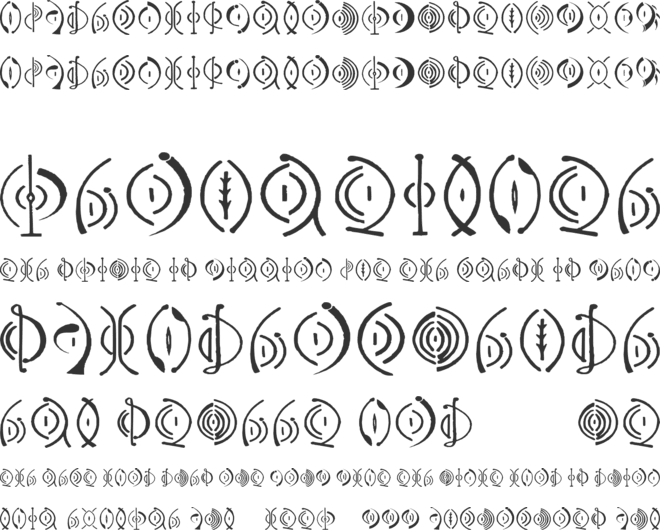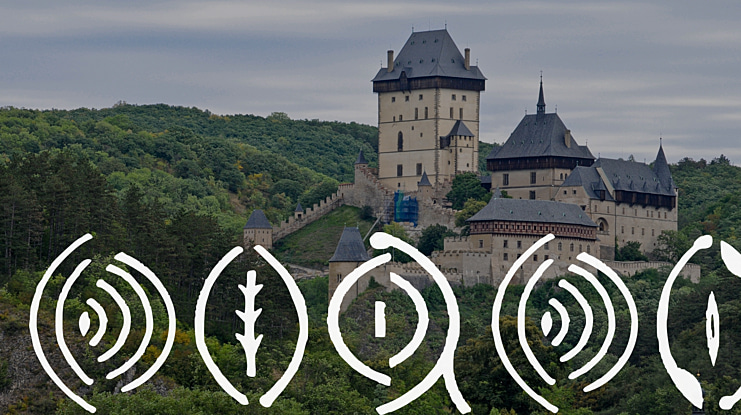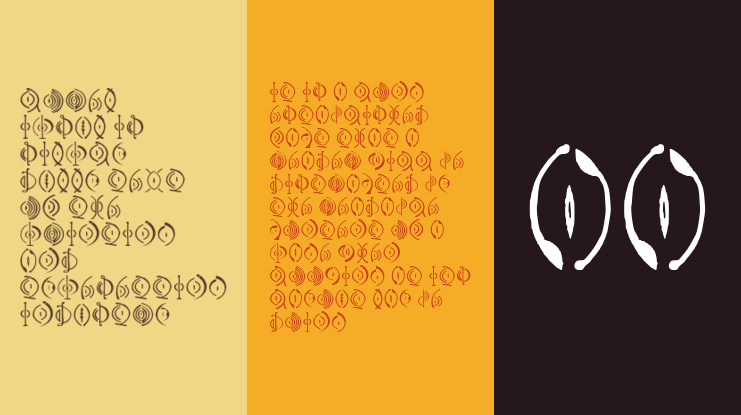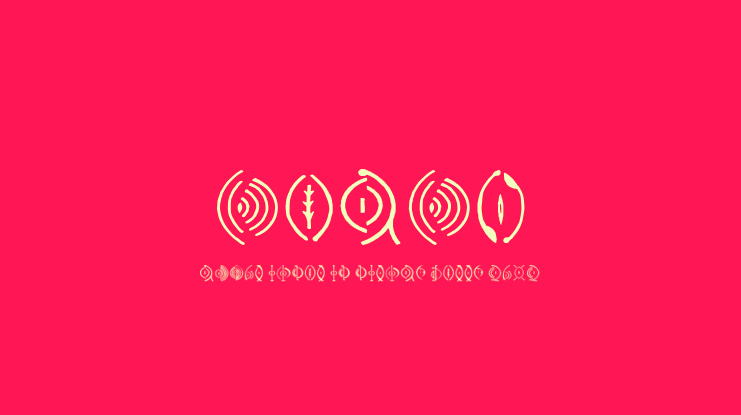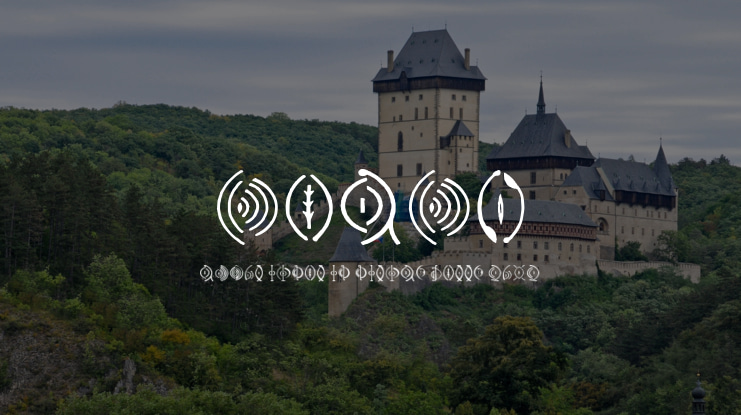
Vulva Font
En mémoire d'un artiste Couserannais " ARIEGE "
Voir son uvre au Musée de l'Affabuloscope 09290 Le Mas-d'Azil.
Le Musée de l'Affabuloscope est un musée consacré à luvre du sculpteur Claudius de Cap Blanc et situé au Mas d'Azil en Ariège. Il dispose d'un espace d'exposition de 1500m²